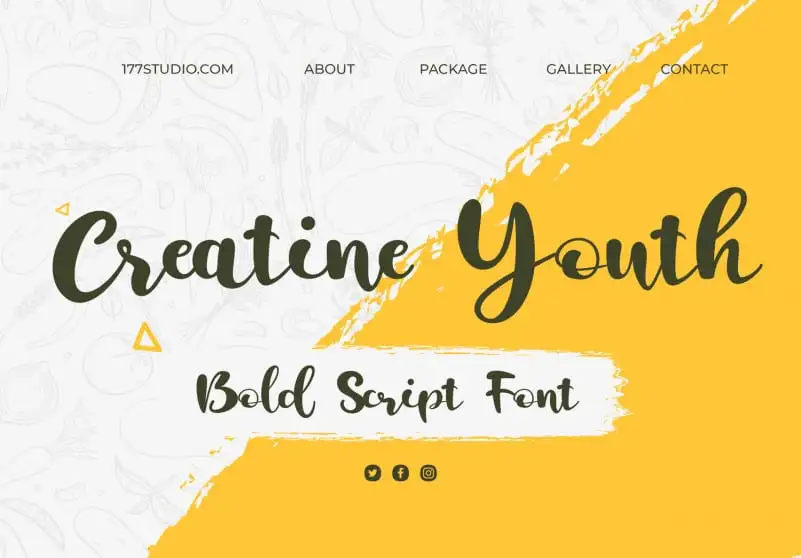
Creatine Youth | Bold Script Font – Download Grátis
A fonte ‘Creatine Youth | Bold Script Font’ é uma nova escolha para designers que buscam dar autenticidade às suas criações digitais. Esse bold script oferece um visual robusto e profissional, com alternativas contextualizadas que permitem que seu design se pareça com escrita a mão. Esta fonte perfeita para projetos criativos e de alto nível. Ela é especialmente adequada para títulos como assinaturas, cartões de selo, logotipos, citações de revistas ou livros, cabeçalhos de sites, roupas de marca, embalagens e muito mais. Seu design autêntico à mão vai dar uma sensação cuidadosa às suas criações, tornando-a uma fonte imprescindível para qualquer projeto de design que deseja transmitir profissionalismo sem perder a personalidade. Não hesite em explorar todas as possibilidades criativas e imprimi-las no seu próximo projeto.